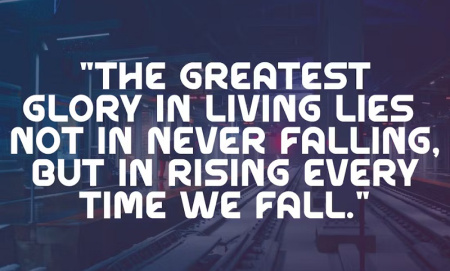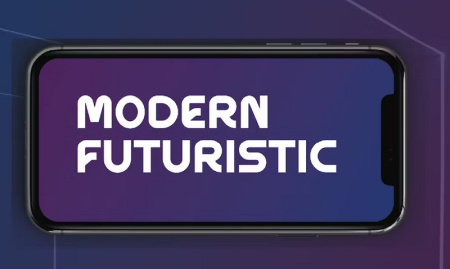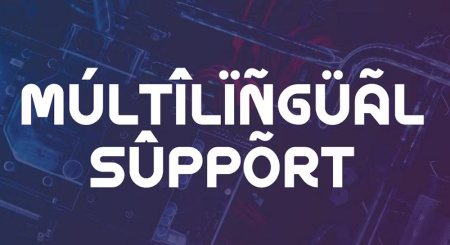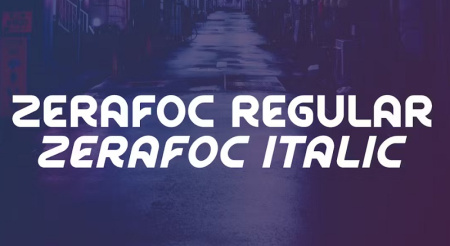
فونت انگلیسی آینده نگر Zerafoc
فونت انگلیسی آینده نگر Zerafoc یک فونت نمایشی آینده نگرانه با طراحی زیبا است. ظاهر زیبا و جذاب آن را به انتخابی عالی برای لوگوها، برندسازی، دعوتنامه ها، لوازم التحریر، طرح های عروسی، پست های رسانه های اجتماعی و موارد دیگر تبدیل می کند. برای مشاهده تصاویر مطلب و دانلود فونت در ادامه مطلب همراه جی اف ایکس دانلود شوید.
✅ نام فونت انگلیسی: Zerafoc